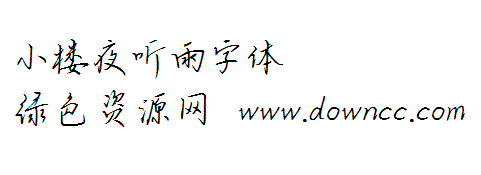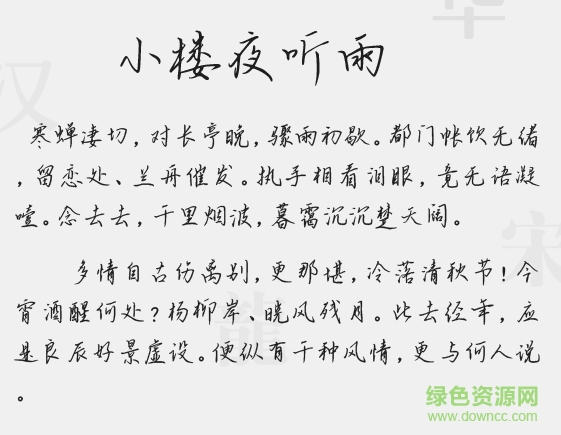
小樓夜聽(tīng)雨體
小樓夜聽(tīng)雨字體是一款時(shí)尚的現(xiàn)代中英文字體軟件,頗有一種草書(shū)的感覺(jué),整體效果不拘章法,象征著自由,用于藝術(shù)設(shè)計(jì)再合適不過(guò)了,歡迎到綠色資源網(wǎng)下載!
小樓夜聽(tīng)雨字體秀麗柔美,優(yōu)美清新,線條流暢,給人以華麗柔美之感,此種類型的字體,適用于女用化妝品、飾品、日常生活用品、服務(wù)業(yè)等主題。
小樓夜聽(tīng)雨字體
小樓夜聽(tīng)雨屬于手寫(xiě)類字體,字體筆畫(huà)細(xì)膩,隱約透露出一股超然灑脫的氣息,隨心所欲,喜歡這款字體的朋友可免費(fèi)下載學(xué)習(xí),切勿用于商業(yè)用途!